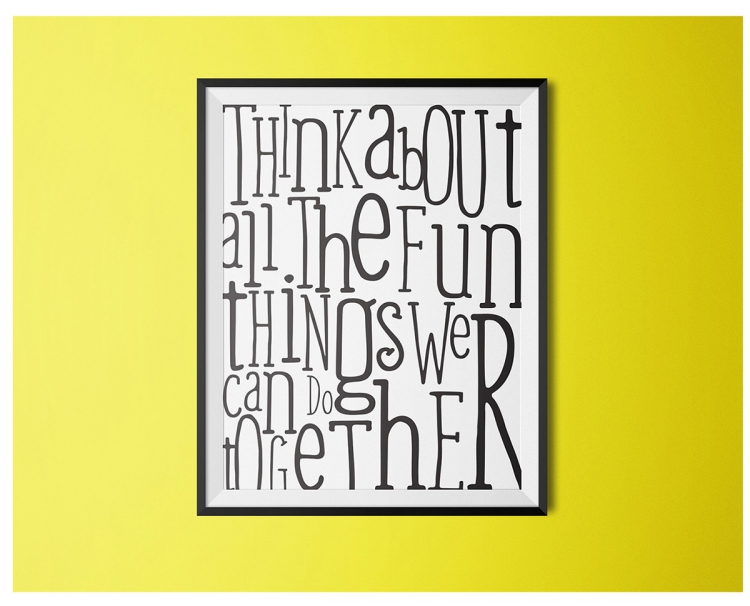
Weem 2019.03.24 2016.12.05Weemは、モダンなデザイの手書き風英語フォントです。おしゃれなセリフ体で、アートや冊子、ショッピングバックまで幅広い場面で活躍します。ライセンス無料で使える商用可のフリーフォントです。ダウンロードWeem当サイトはフリーフォントの紹介サイトです。フォントを利用の際には、各サイトで最新の利用条件やライセンスを必ず確認してください。フォント情報ライセンス商用可カテゴリー英語 > ハンドライトタグおしゃれ、かっこいい、手書き風、クール